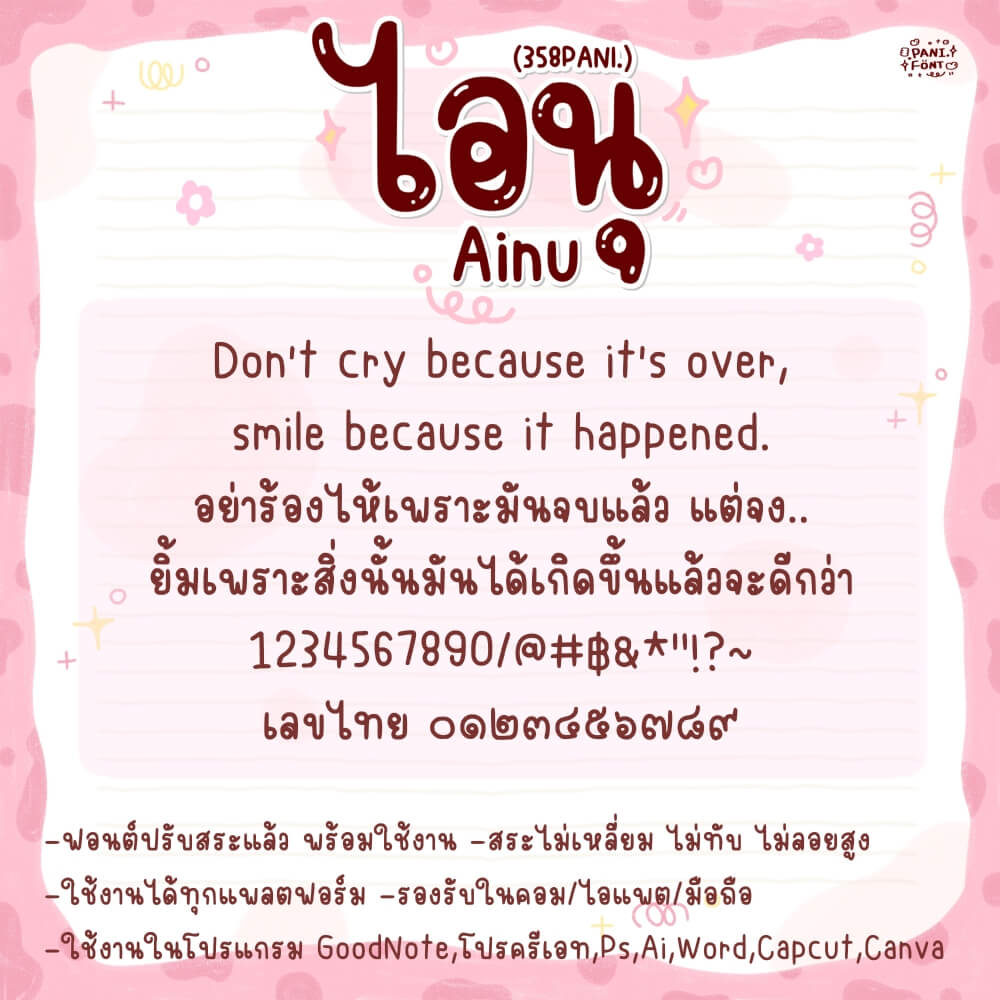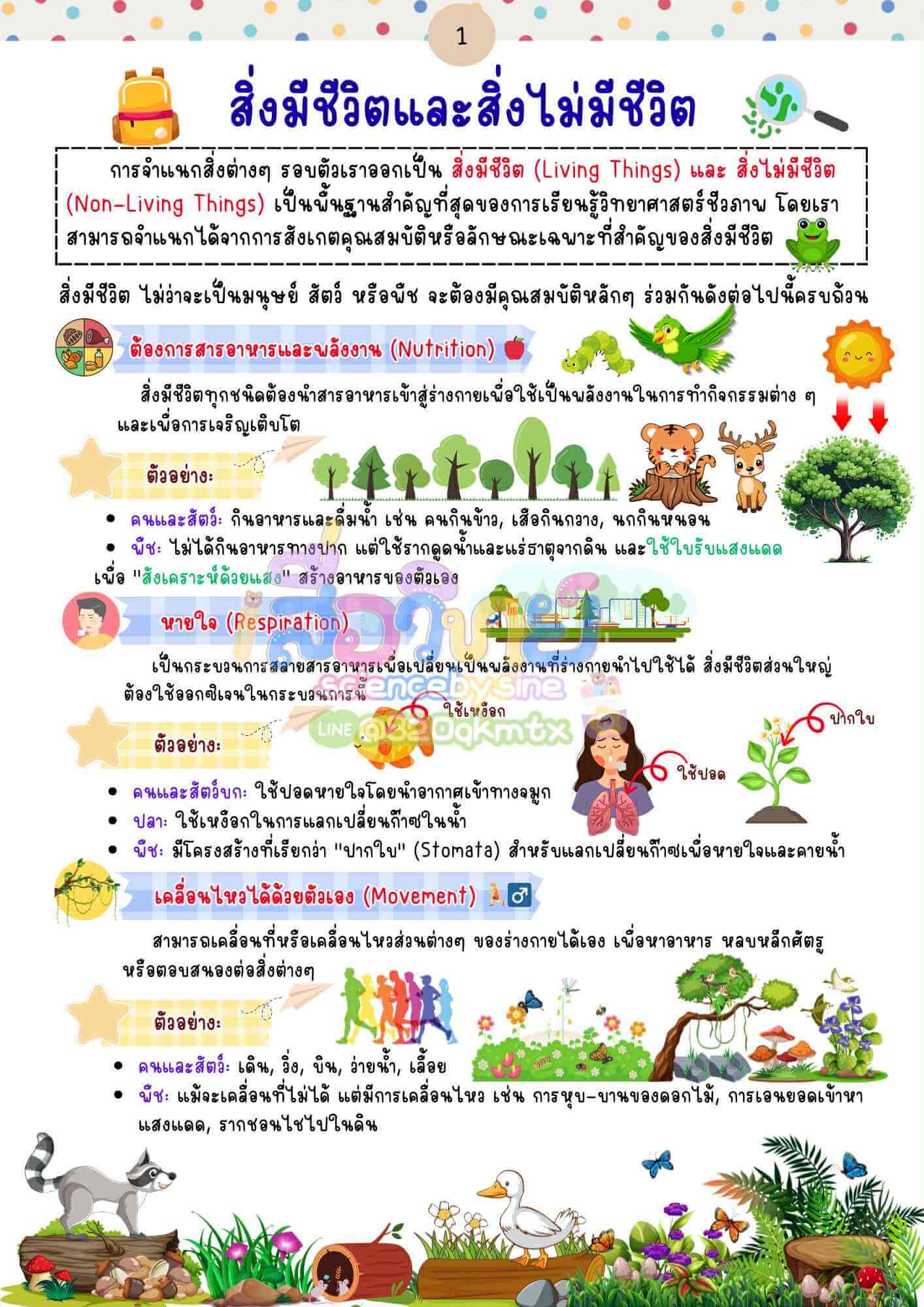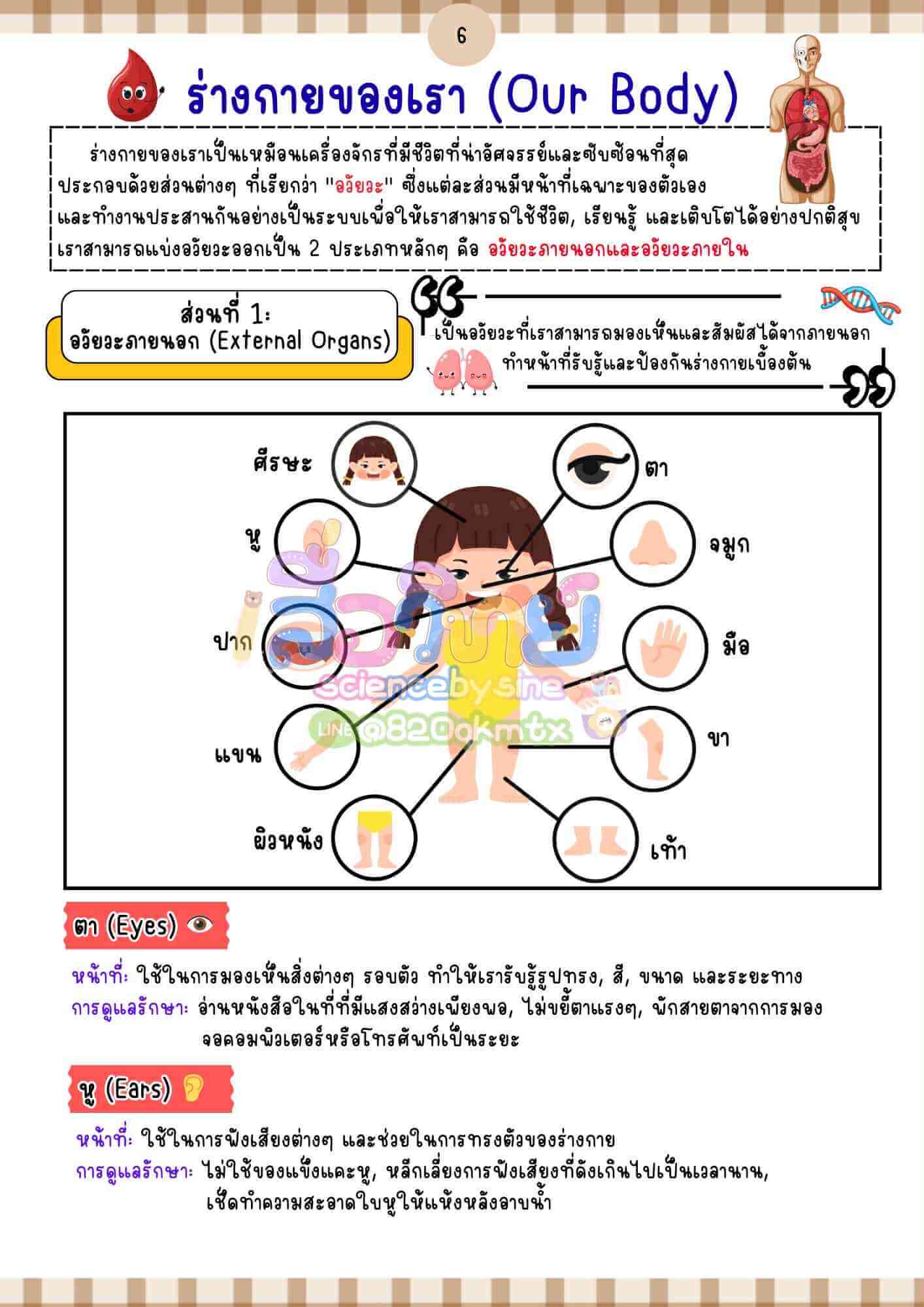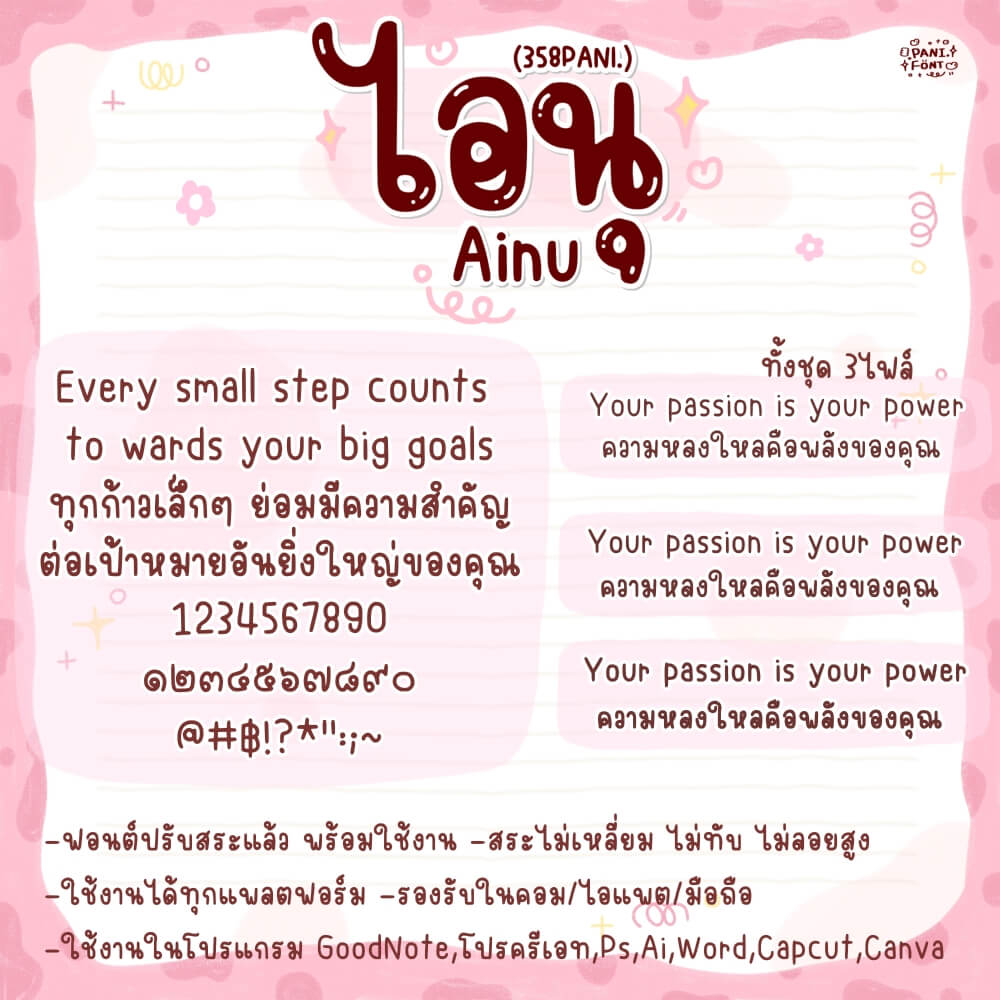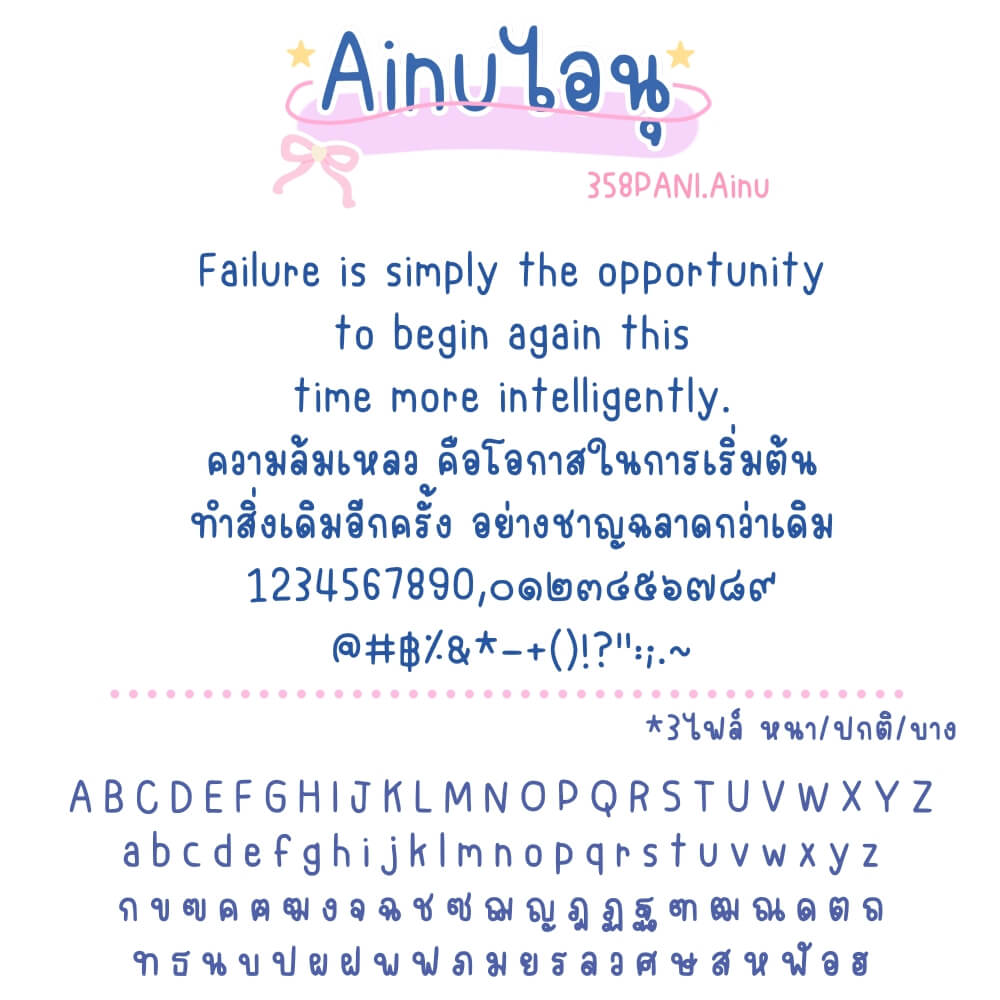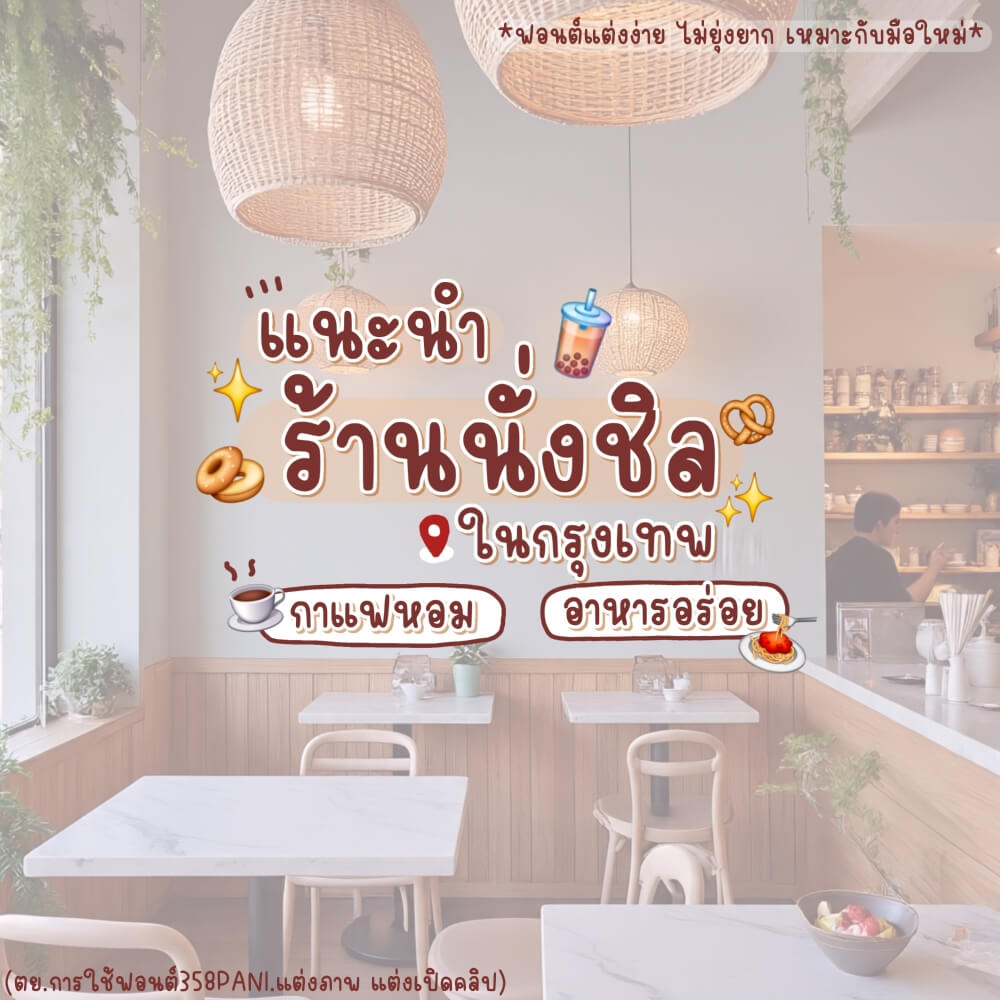
358PANI.ไอนุ
ฟอนต์ 358PANI.ไอนุ – ฟอนต์อ่านง่าย เรียบร้อย ตัวอักษรชัดเจน เหมาะกับงานหลากหลาย ตั้งเครื่อง จดโน้ต ใช้อ่านรายละเอียด ทำคลิปนายหน้า แต่งภาพสินค้า ไม่ต้องแต่งเยอะ ก็ดูสวยน่ารัก
*ฟอนต์แต่งง่าย ไม่ยุ่งยาก เหมาะกับมือใหม่*